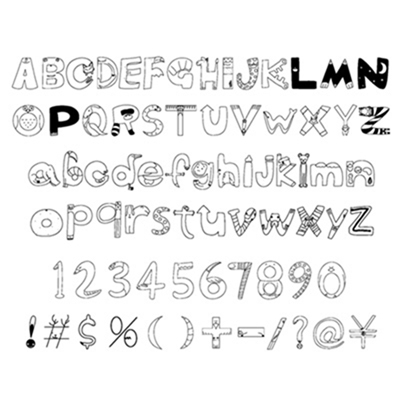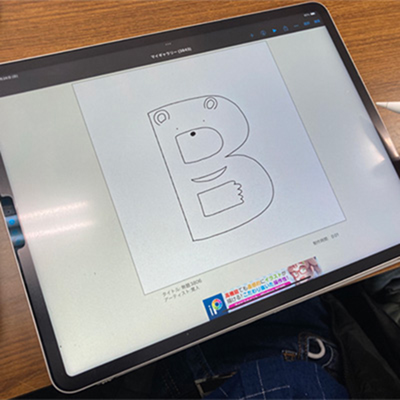
ごちゃまぜフォントABC
動物がフォントになってごちゃまぜフォント!
Artist渡部寛人
Designerさとうひろゆき
Organizationあそ美
ごちゃまぜフォントABCは、英単語の頭文字を僕の大好きな動物や食べ物などと合体させて作りました。このフォントを見て笑顔になってもらえたら嬉しいです。何がごちゃまぜしているか当ててみてください。(渡部寛人)
本当に素敵なフォント。悩むことなくスラスラ書いていました。ぜひ、一つ一つの文字をみて欲しいです。(さとうひろゆき)
普段はiPadを使って絵や文字を描いています。見る側がほっこりと笑顔になる絵で、みんなを喜ばせてくれています。(あそ美)